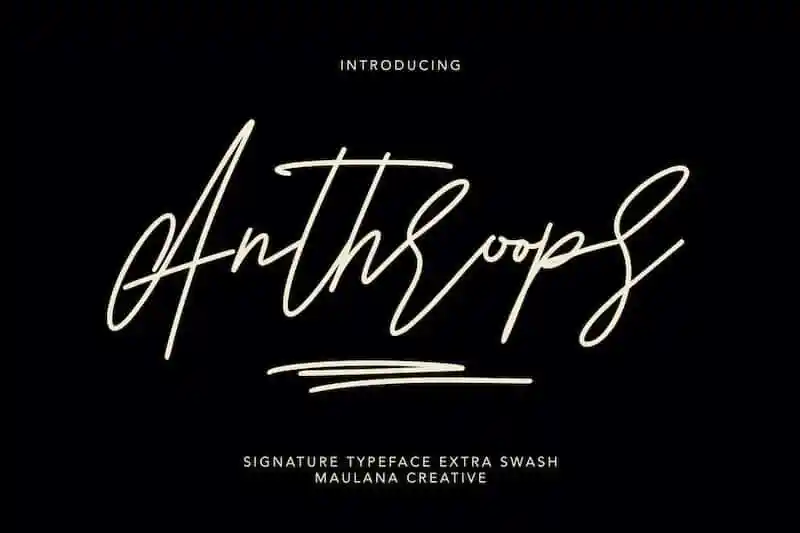
Anthroops Handwritten Font – Fonte Grátis
Anthroops Handwritten Font
A Anthroops Handwritten Font é uma escolha perfeita para quem procura uma fonte que transmite elegância e naturalidade. Desenvolvida pelo designer 99designs, esta fonte monoline possui um toque natural de escrita humana. E se você está buscando incorporar em seu design elementos únicos, detalhes aprimorados e um toque refinado, essa é sua font. A Anthroops Handwritten Font não apenas será uma escolha excelente para assinaturas, identidades visuais, logotipos ou capas de livros, mas também será ideal para criações de sites, cabeçalhos de roupas, embalagens e até mesmo materiais publicitários. O seu design elegante e natural está aqui para garantir um toque único em qualquer projeto. Quer experimentar a essência da autenticidade e do originalismo? A Anthroops Handwritten Font é uma escolha inteligente para quem valoriza detalhes e tem um gosto refinado no design. Não perca esta oportunidade de deixar seus projetos ainda mais impressionantes com a elegância natural desta fonte.